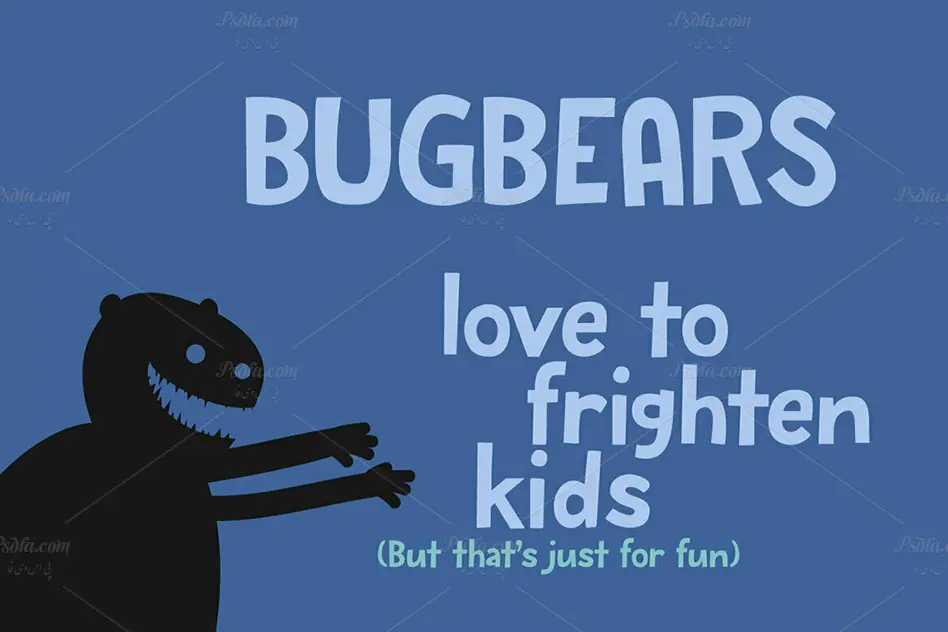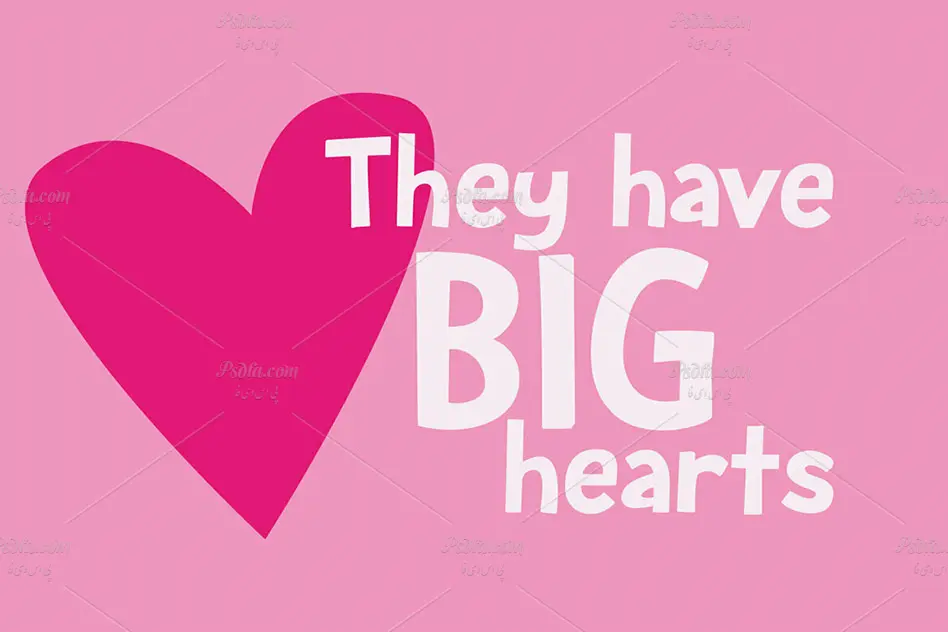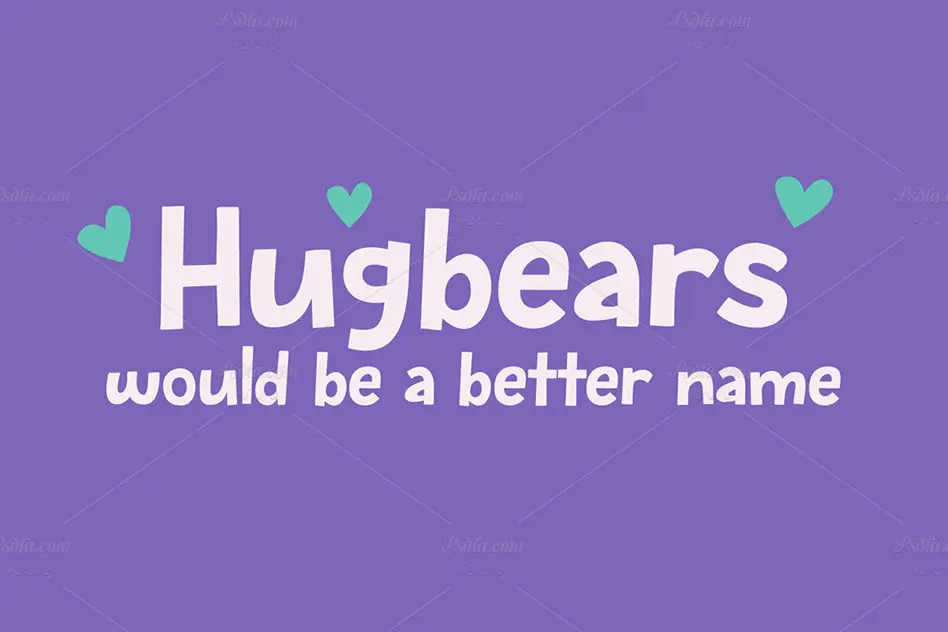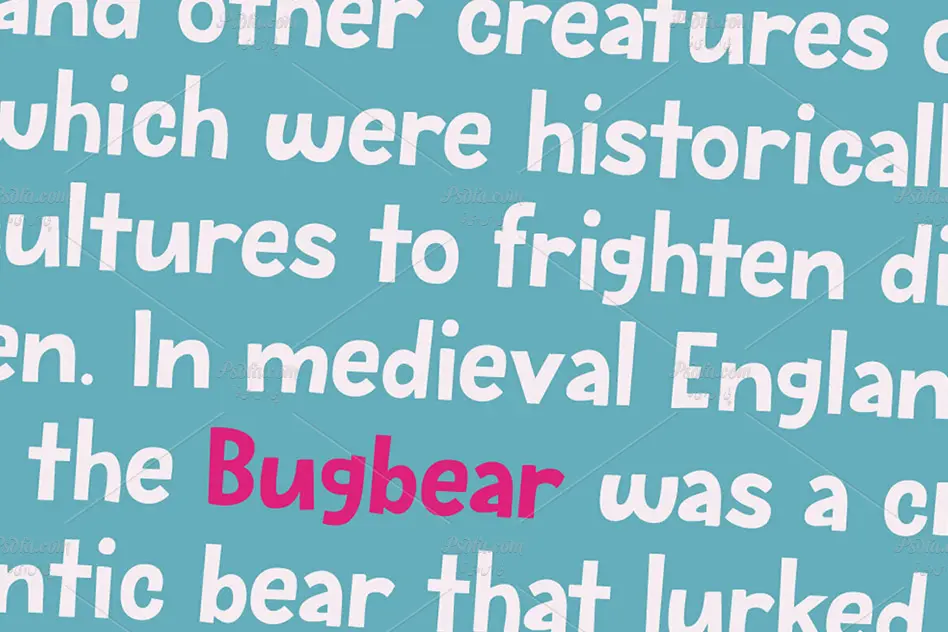
فونت کارتونی Bugbear مناسب برای طرح های کودکانه
فونت کارتونی Bugbear
در این مطلب شاهد فونت کارتونی Bugbear مناسب جهت استفاده در طرح های کودکانه می باشید. این فونت زیبا در قالب 2 فایل otf بر روی سایت بارگذاری شده است که با نصب این دو فایل در پوشه فونت های سیستم قادر به استفاده از آن در تمام نرم افزارهای گرافیکی و ویرایشگر متن از جمله نرم افزار فتوشاپ ، افترافکت ، مجموعه نرم افزار آفیس و … خواهید بود. فونت Bugbear در دو وزن معمولی (Regular) و مورب (Italic) طراحی شده است که می توانید از آن در طراحی انواع طرح های گرافیکی همچون طراحی کارت ویزیت ، تراکت ، بروشور ، بنر ، انواع پوستر و … استفاده کنید.